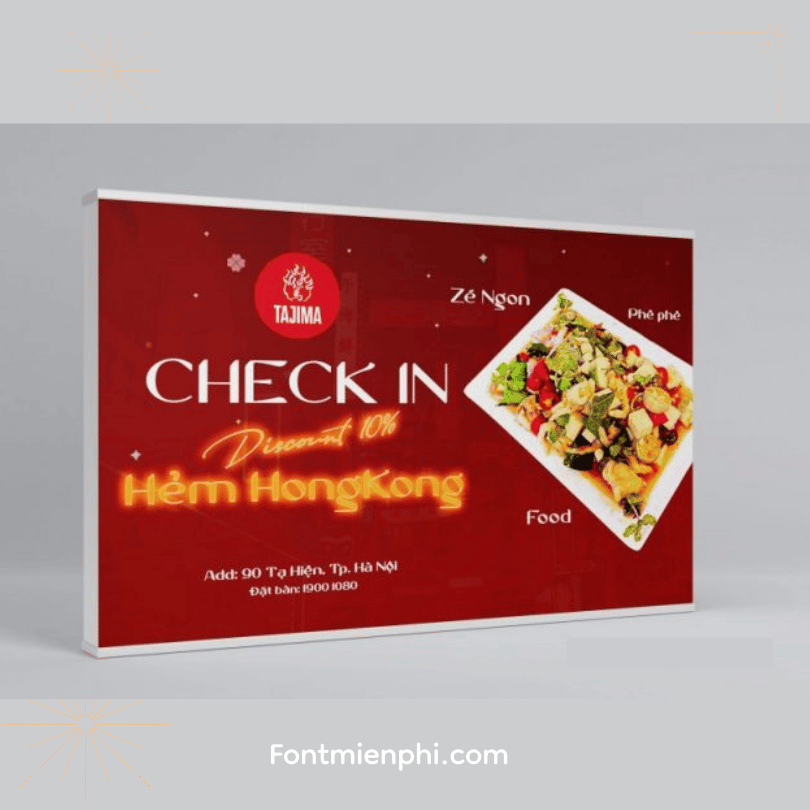
Việt hóa font 1FTV thiết kế ẩm thực 2
Việt hóa font 1FTV thiết kế ẩm thực 2  – Phong Cách Độc Đáo Cho Thiết Kế Ẩm Thực
Font 1FTV Ẩm Thực 2 đã được Việt hóa hoàn chỉnh, là lựa chọn lý tưởng cho các thiết kế liên quan đến ẩm thực, nhà hàng, quán cafe hay thực phẩm. Với nét chữ độc đáo kết hợp giữa phong cách hiện đại và nét vẽ tay thủ công, font mang lại cảm giác gần gũi, ấm cúng nhưng vẫn nổi bật.
Đặc điểm nổi bật:
✔ Hỗ trợ đầy đủ dấu tiếng Việt
✔ Thiết kế tinh tế, phù hợp menu, poster quảng cáo
✔ Nét chữ độc đáo, dễ đọc nhưng vẫn sáng tạo